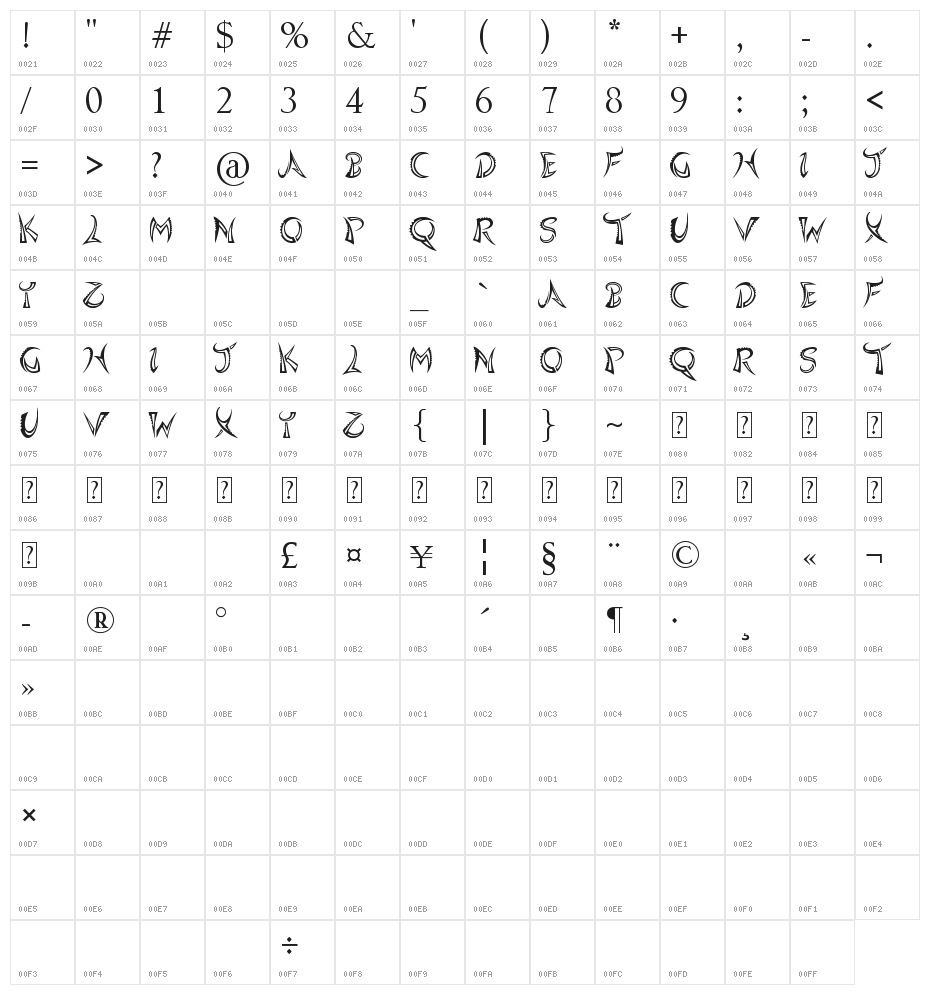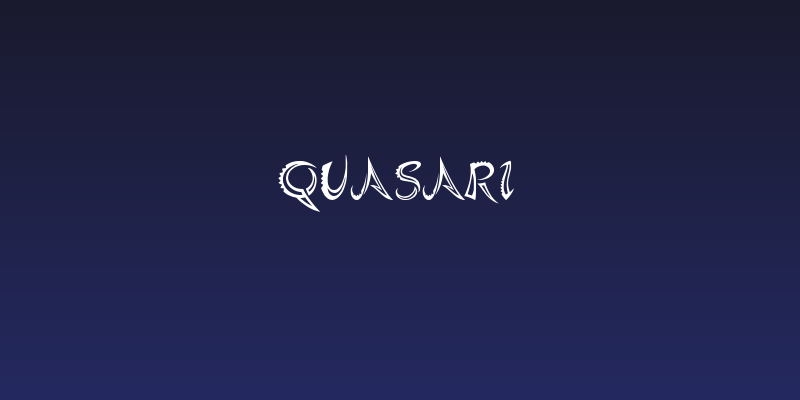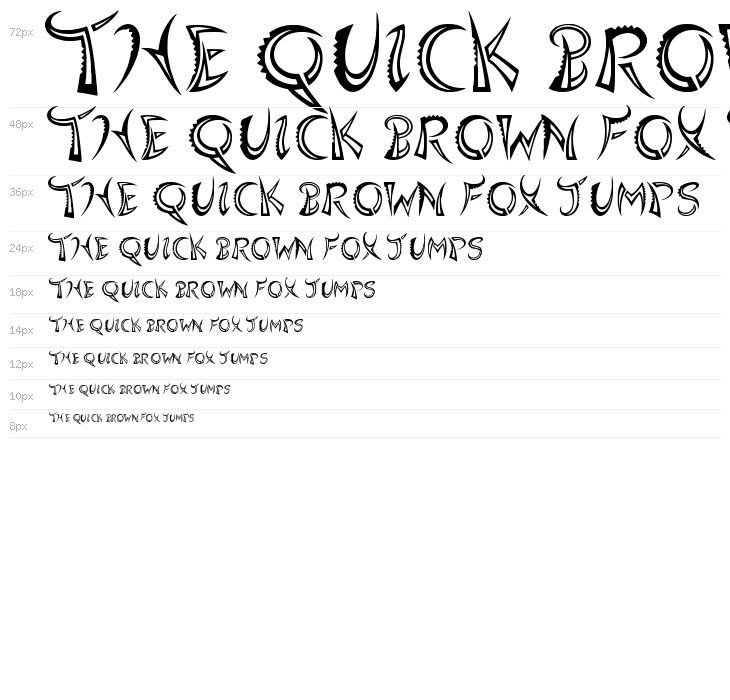
Quasari Font
✎ Stylish
| 分类 | Stylish |
| 整体风格 | Modern, Decorative |
| 推荐项目 | Ideal for album covers, posters, branding for edgy or alternative products, and any design needing a bold statement. |